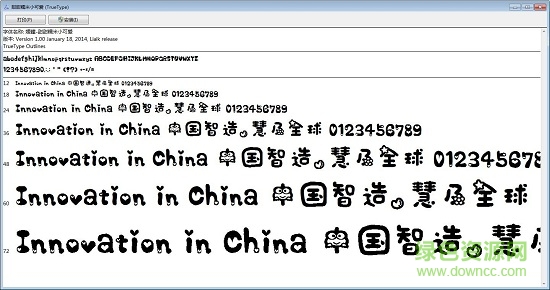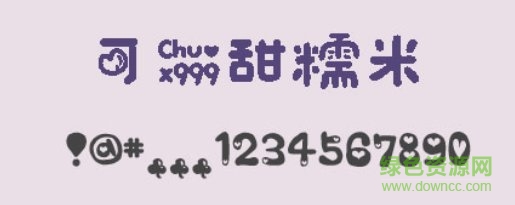
可愛(ài)甜糯米字體是一款以可愛(ài)為主打造的字體,字體在設(shè)計(jì)中增加了部分素材,無(wú)論是在漢字,字幕或者是其他的符號(hào),在顯示中都會(huì)增加部分可愛(ài)素材,看起來(lái)更加的俏皮,需要的用戶快來(lái)綠色資源網(wǎng)下載吧!
可愛(ài)甜糯米字體是一款非??蓯?ài)的中文卡通字體,擁有與非常圓潤(rùn)的字體外形,粗短風(fēng)格的字體筆畫(huà),將心形、青蛙、花朵、星星等圖案加入到字體中,并且完全與字體融合,絲毫不影響漢字識(shí)別度,支持簡(jiǎn)體漢字、拼音字母、數(shù)字符號(hào)等輸出格式,給你帶來(lái)更好的顯示效果。